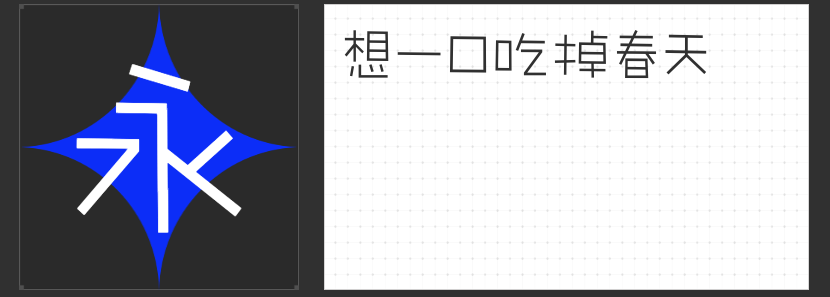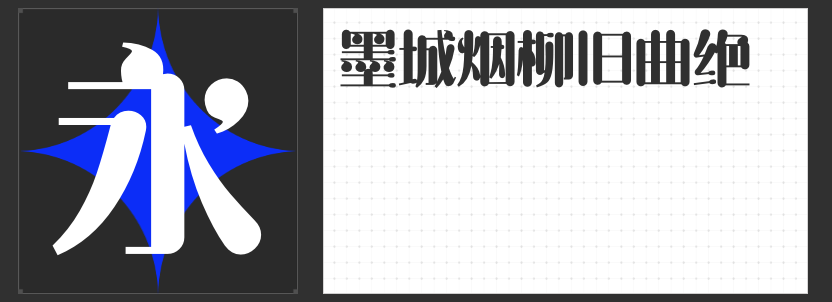
四款影视设计专属字体推荐:以字形构筑视觉叙事新维度
在影视设计的视觉语言体系中,字体不仅是信息传递的载体,更是情感表达与氛围营造的关键元素。一款契合主题的字体,能瞬间强化画面张力,引导观众沉浸于故事情境。本文精选四款风格独特的付费字体,从灵动俏皮到严谨优雅,为影视海报、片头设计、动态标题等场景提供多元选择。
一、励字敲可爱简 细体
这款字体以直线勾勒为核心,通过省略非关键笔画与圆润化处理,打造出介于书写与绘画之间的独特形态。其略带稚拙的线条既保留了文字的辨识度,又赋予画面轻盈的呼吸感。细体设计在保持视觉清爽的同时,通过笔触的断续与收放传递手写的柔软与温度,尤其适合动画电影、青春题材或儿童向影视作品的视觉包装,为画面注入天真烂漫的想象力。
二、字恋狂嗨玩简
以粗壮方块字形为基底,搭配重心下沉的笨拙结构,这款字体如同孩童堆叠的积木,自带憨态可掬的喜剧感。笔画间的几何切割与留白处理,既强化了字体的视觉冲击力,又通过“不完美”的形态传递无拘无束的玩趣精神。适用于喜剧电影、综艺节目或奇幻题材的片头设计,能快速打破严肃氛围,拉近与观众的心理距离。
三、励字超级勇士简 常规
作为一款融合严谨结构与柔和气质的黑体变体,其笔画采用现代几何化设计,通过微妙的弧度转折与均衡的负空间,营造出舒适而不失力度的视觉节奏。常规字重既保证了远距离阅读的清晰性,又通过细节处的圆角处理弱化机械感,适合科幻、悬疑或文艺类影视作品的标题设计,传递理性与感性交织的独特气质。
四、励字明姿简
这款美术字以竖粗横细的经典结构为基础,融入几何图形的创意变形,笔画末端如魔法棒划过的轨迹般灵动飞扬。圆润的转角与动态的线条组合,既保留了传统美术字的仪式感,又通过夸张的视觉比例赋予节日般的欢愉氛围。尤其适用于贺岁片、音乐节或跨年晚会的视觉设计,瞬间点燃观众的期待情绪。
四款字体各具美学基因,或以童趣破局,或以几何制胜,共同构建起影视设计的字形宇宙。设计师可根据作品调性,灵活调用字体的情感属性,让文字成为叙事的第一帧画面。